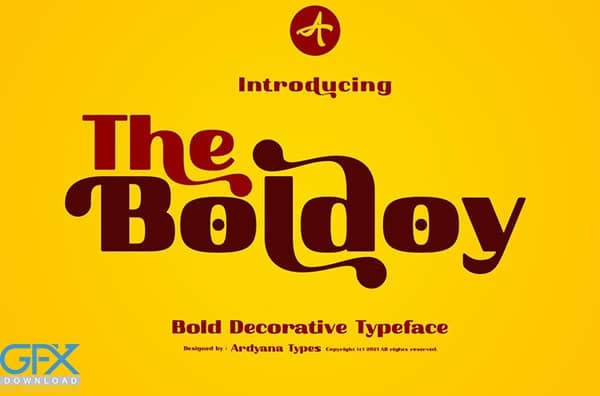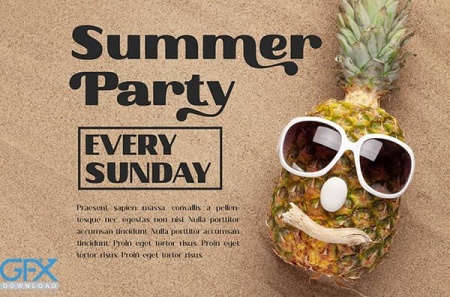
دانلود رایگان فونت بولد Boldoy
در این مطلب شاهد فونت بسیار زیبا و جذاب با استایل بولد می باشید که به صورت کاملا رایگان در جی اف ایکس دانلود برای دانلود قرار گرفته است. این یک فونت پر انرژی و جذاب است و در سبک های مختلف طراحی مانند مسافرت ، آرم ، پوسترهای مراسم و بسیاری از پروژه های طراحی دیگر نیز قابل خواندن و استفاده است. با دانلود فونت بولد Boldoy شما می توانید برای چاپ و صفحه نمایش از این فونت رایگان استفاده نمایید.